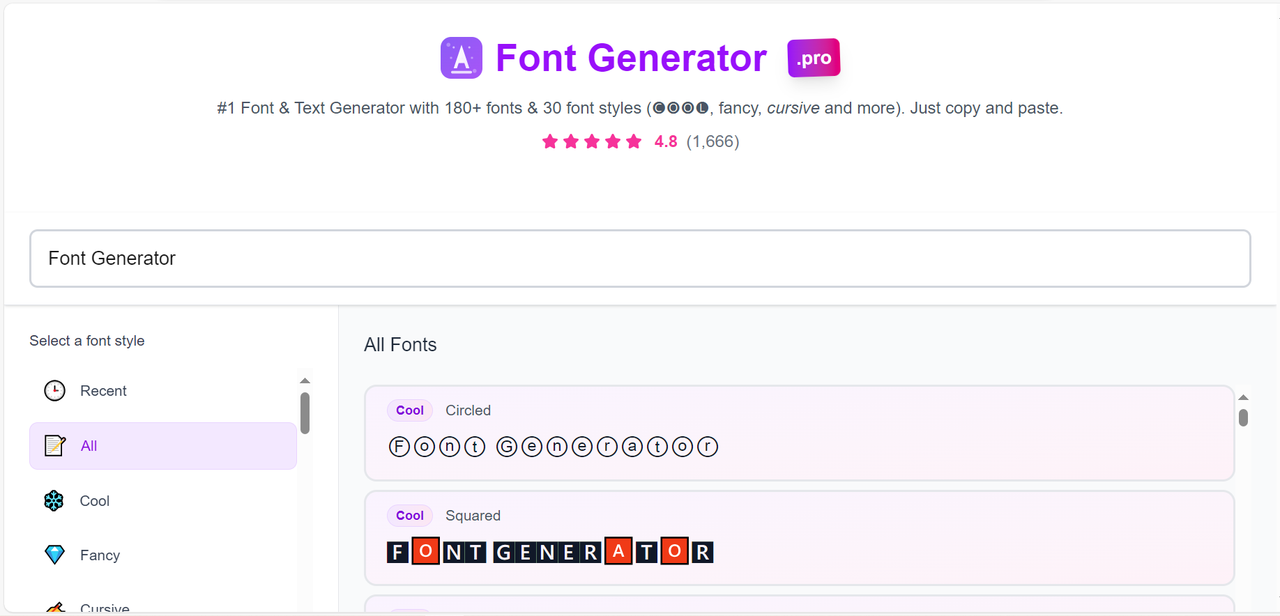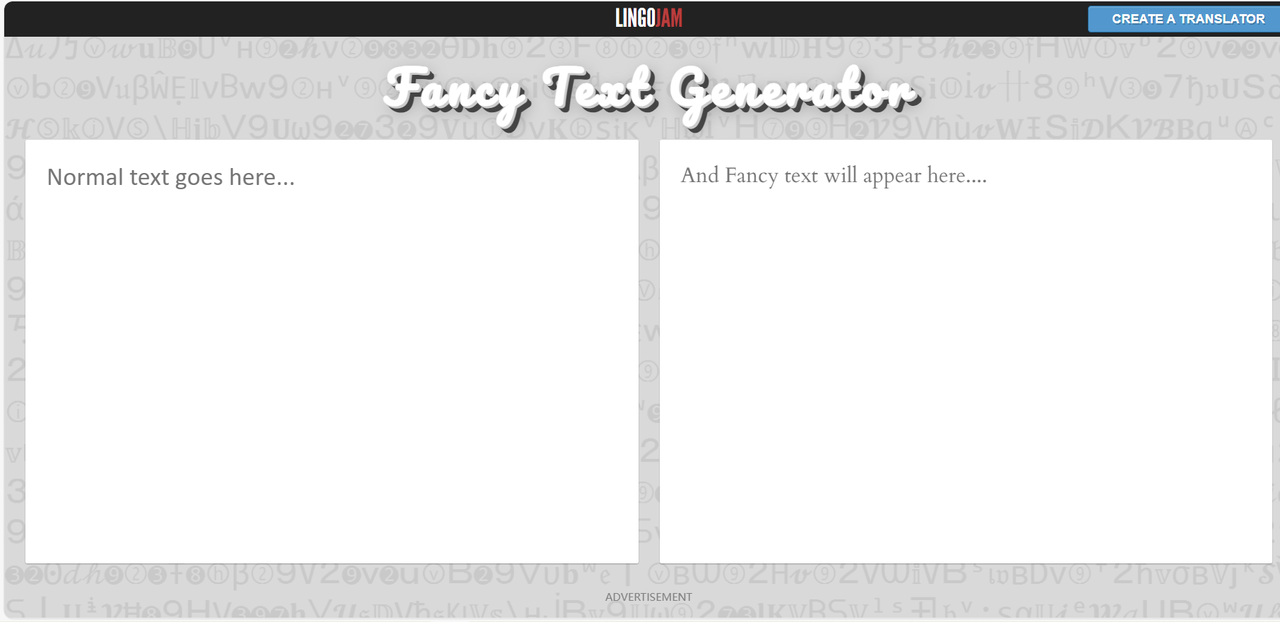
在线文字转换器:6款免费工具合集
在数字化媒体飞速发展的时代,普通的系统文字很难满足人们对个性化的追求,优质且富有设计感的文字不仅能吸引大众的眼球,还能提升内容的可读性以及用户参与度。无论你是设计师、自媒体人还是普通用户,找到合适的在线文字转换器都能可以让你事半功倍,轻松实现文字转换。本文将介绍 6 款免费的在线文字转换器,都是亲身经历测评过的哦,哪怕你是新手小白或者跨行体验者,这些文字转换器的操作简单,能帮助你快速生成想要的品牌标题、视频字体、海报标题等等,一起来看一下吧。
一、字由
字由作为腾讯、京东、小红书、华为等国内头部大品牌的合作伙伴,注册用户远超 2000 万,成为很多设计师信赖首选的免费字体工具。它不仅仅能实现在线文字转换,同样能对字体进行管理。字由的 AI 字体功能是我非常喜欢且经常使用的,甚至不需要你动脑操作什么,只要选出一个你喜欢的文字效果,点击做同款,就能几秒内实现艺术字、特效字的转换,方便快捷且实用!
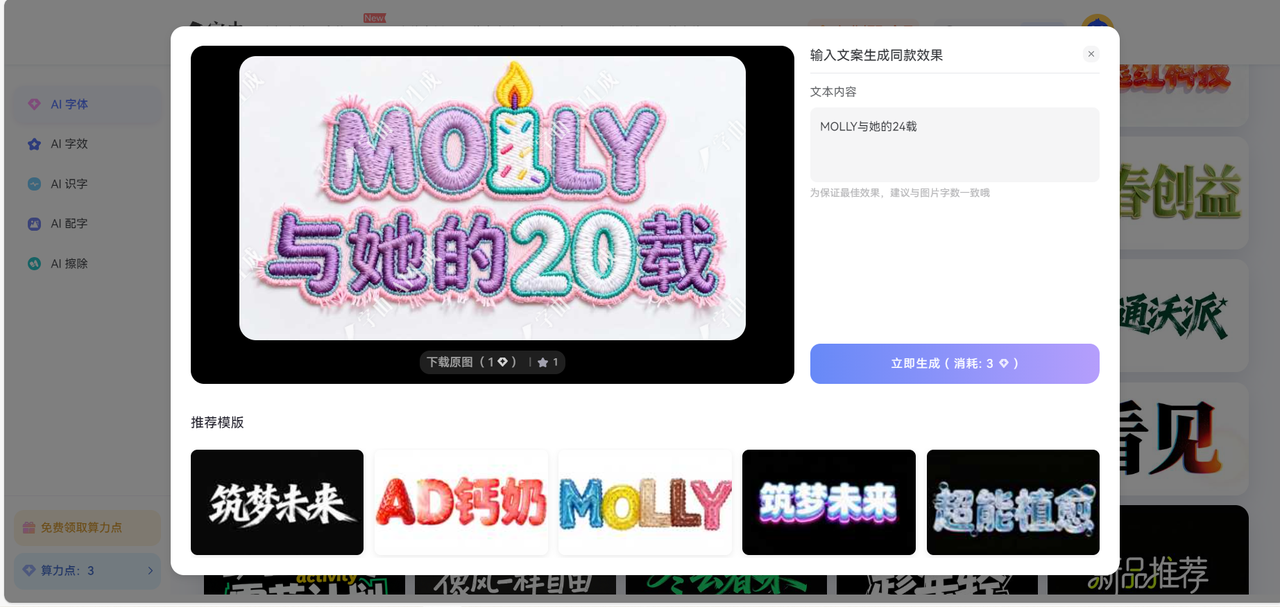
除此之外,字由客户端还可以实现在 PS、Sketch、AI、Figma、Sketch 等设计软件中的字体一键转换。你在设计软件选中需要转换的文字,在字由客户端激活需使用字体,即可完成字体之间的转换,无需下载字体,为你的电脑节省更多的内存。
二、 Font Generator Pro
Font Generator Pro 是常用的在线文字转换器,它拥有 200+ 种独特的字体样式,还能生成特殊字符。用户不仅可以在线转换英文字母,还能生成各种装饰边框、特殊符号。转换后的文字可以直接复制粘贴到大部分的社交媒体平台、网页应用、文档编辑器,同样可以继续保持该文字的可编辑性,这一点还是非常方便的。但是 Font Generator Pro 转换中文的效果不明显,比较适合在线转换英文,而且它的字体库更新很频繁哦,也支持批量转换,能节省你的很多操作时间。
三、LingoJam
相较于其他在线文字转换器,LingoJam 最大的优势在于可以支持多语言的文字转换,比如中文、英语、法语、德语等多种拉丁字母语言。除了这些基础的文字转换,它还提供字体效果叠加功能,用户可以为文本加上多种视觉效果(阴影、渐变填充、描边等)不过叠加文字效果会影响电脑的运行速度,如果设备系统比较老旧,不建议使用这个功能。另外还需要提醒大家,LingoJam 每天有固定的免费转换字体次数,一般来讲也够个人日常使用了。
四、FontVilla
FontVilla 完美解决了专业设计师和创意工作者的需求,提供高质量字体转换,强调设计的实用性和美观性。借助这款在线文字转换器,你可以创造出 在Facebook、Instagram、游戏用户名及其他社交媒体账号上随处可见的酷炫独特字体。而且操作简单,只需要输入你的文字,然后点击你想使用不到高级字体旁边的复制按钮即可,可以粘贴到任何设计较平台或者文档里。
五、YayText
YayText 主要针对社交媒体的文字进行转换优化,解决了各大平台字体限制的问题,它深入研究不同社交媒体的特点,提供专属的平台字体转换方案。前段时间,YayText 还开发了专门的字体兼容性数据库,里面记录了 100 多种字体在 20 多个主流谁叫平台上的呈现差异。这也就意味着,当你使用该工具转换文字的时候,他会根据不同的平台特性调整字体的选择,确保最大的兼容性,保证转换的字体可以在每个平台使用。不过它的字体样式比上面几款工具保守很多,缺少花哨的艺术字体,且它不能批量处理字体,字体转换需求较大的小伙伴就不要考虑这个工具啦。
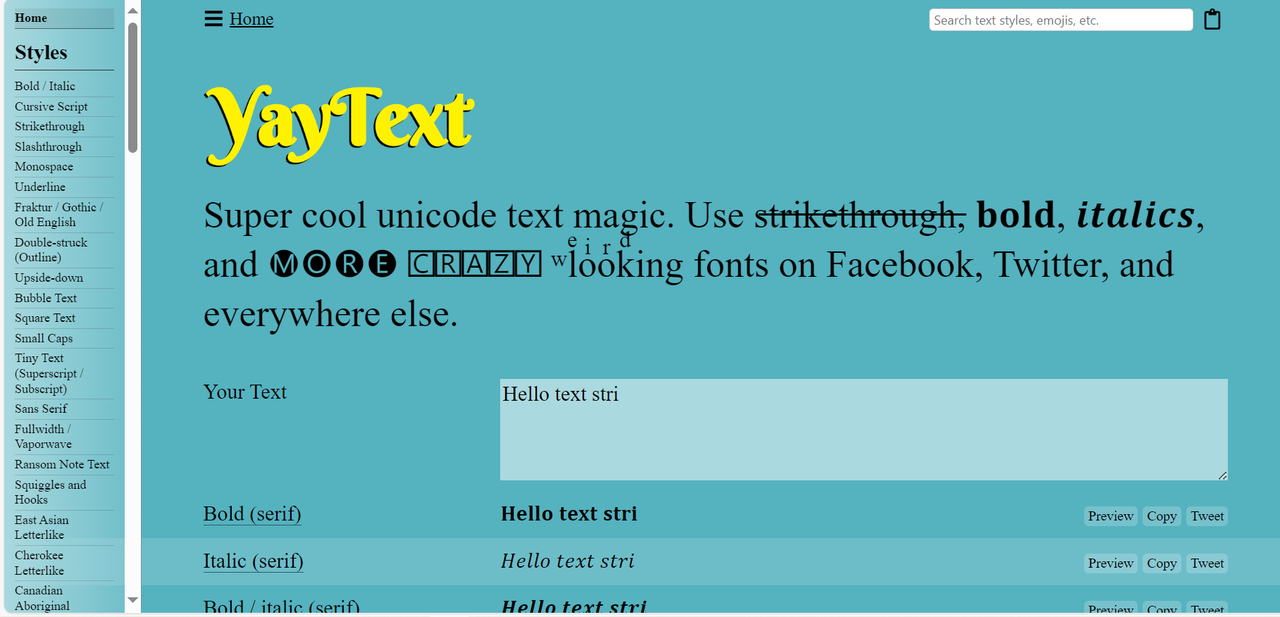
六、Fancy Text Generator
追求艺术效果的设计师朋友们快把 Fancy Text Generator 收藏起来,它专注于艺术性和装饰性的字体转换,非常适合需要吸引眼球的场合。除了静态字体的转换,该工具还提供了丰富的动态字体效果,类似于打字机的效果、霓虹灯闪烁效果、手写动画效果等,能让你的字体更加充满艺术性和设计感。一些比较复杂的文字效果导出格式有限,只适合主屏幕使用。
最值得一提的是,Fancy Text Generator 的字体混合器可以将两种不同的字体特点进行结合,创建出属于你的混合字体。个人认为这个功能比较适合有经验的设计师,艺术效果越复杂,越容易显得杂乱无章,降低可读性,怎么样把这种字体放在一个合适的位置上,需要设计师的时尚敏感度和经验来判断。
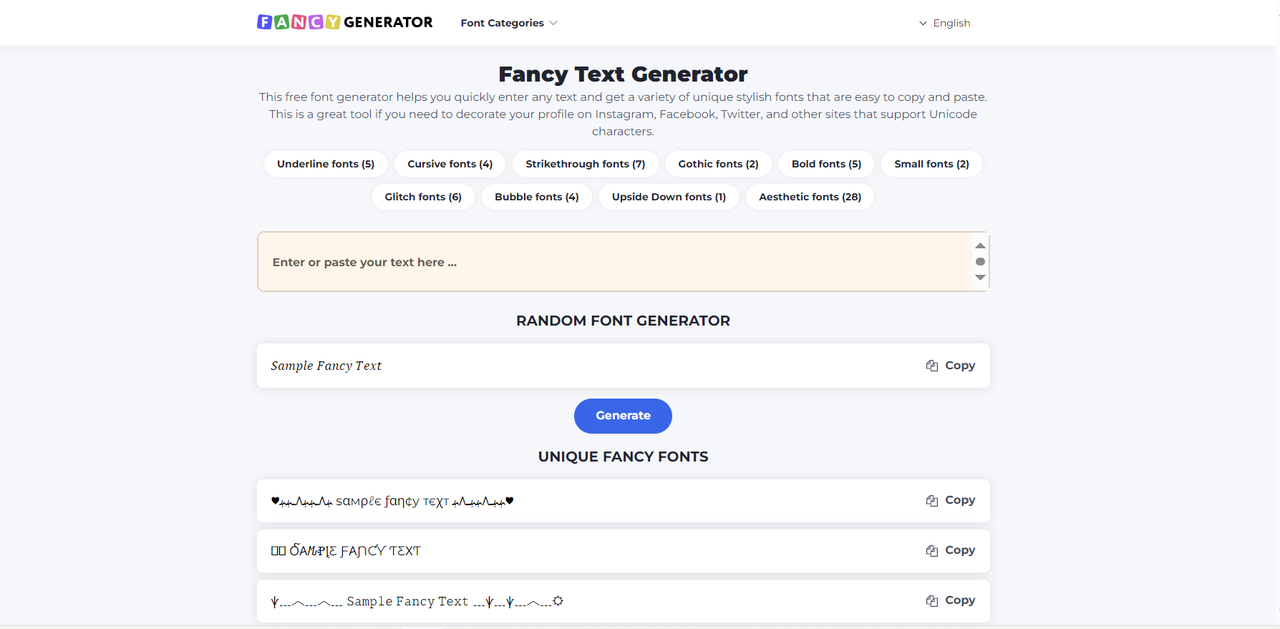
以上介绍的在线文字转换器都各有千秋,关键在于明确你的具体需求和使用场景,才能选出最适合自己的工具。字由可以实现艺术字的转换,也可以在各大设计软件上实现字体转换,功能丰富且好上手;Font Generator Pro 适合转换英文字体和生成特殊字符;多语言内容创作者可以首选 LingoJam;FontVilla 可以根据不同场景推荐适合的炫酷字体;YayText 的平台优化功能可能最为实用;追求艺术效果的设计者可以在 Fancy Text Generator 找到无限灵感。相信有了这些在线文字转换器的帮助,能帮助你创作出更优质的字体哦!